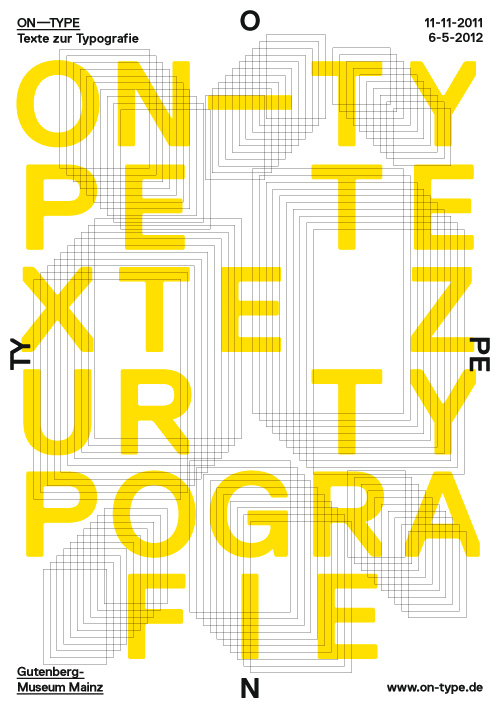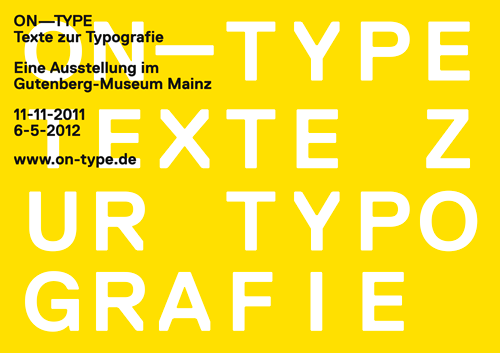
Die Ausstellung »ON–TYPE: Texte zur Typografie« präsentiert Klassiker der Typografiegeschichte des 20. Jahrhunderts und aktuelle Beispiele, auch aus den Beständen des Gutenberg-Museum Mainz und der Gutenberg-Bibliothek. Zum ersten Mal wird eine Sammlung von Grundlagentexten über die Schriftgestaltung zusammengestellt und den Besuchern vorgestellt.
Aus dem Pressetext: Typografie – die kleine Schwester der Sprache – ist ein Fundament unserer Kultur. Sie ist gegenwärtig. Sie gestaltet unser alltägliches Leben in der Zeitung, im Buch, auf den Preisschildern der Supermärkte und wird doch höchstens unterbewusst wahrgenommen.
Wenn wir als Kind die Buchstaben einmal erlernt haben, erschließen uns die Schriftzeichen die geschriebene Welt. Ähnlich wie beim Gehen oder Fahrradfahren lesen wir, nach ausreichender Übung, nahezu automatisch. Die Schrift nehmen wir dabei in der Regel kaum wahr – und doch besitzt jeder Leser reiche Erfahrungen mit der Schrift und jeder Schreibende hat auf seinem Computer Zugang zu einer Fülle unterschiedlicher Schriften.
Schriftliebhaber, Philosophen, Typografen und Schriftgestalter haben schon immer über Typografie weit mehr geschrieben, gestritten und gedacht als allgemein bekannt. Die Ausstellung »ON–TYPE: Texte zur Typografie« versammelt Thesen, Manifeste und Standortbestimmungen zur Typografie des 20. Jahrhunderts im deutschsprachigen Raum. Sie präsentiert Schriftmuster und Typo-Insider-Magazine, zeigt wichtige Protagonisten und Diskurse der Typografiegeschichte, bildet aber auch hitzige Diskussionen ab: über »deutsche Schrift«, den »modernen Menschen«, Lesbarkeit, Kleinschreibung oder die Folgen der Digitalisierung. Die Ausstellung vermittelt die Faszination der Schriftgestaltung. Eine eigens gestaltete Lese-Lounge, interaktive Anwendungen und Hörbücher laden ein zu einer intensiven Lektüre und Anschauung. Begleitet wird die Ausstellung von zahlreichen Vorträgen, Lesungen, Filmen, Workshops und einer Publikation.
Ein Projekt des Gutenberg-Museums Mainz Gutenberg-Museum Mainz in Kooperation mit Kommunikationsdesignern der Fachhochschule Mainz und des Instituts Designlabor-Gutenberg im Rahmen »Mainz – Stadt der Wissenschaft 2011«.
ON–TYPE – Texte zur Typografie
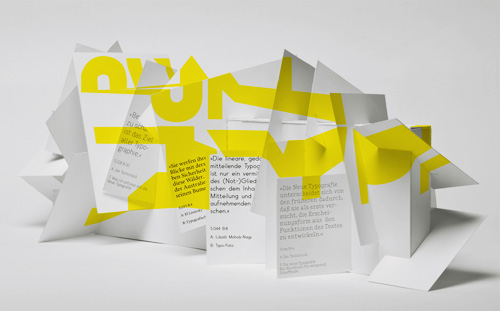
Während der Dauer der Ausstellung ON-TYPE gibt es ein großes Rahmenprogramm, das wir an dieser Stelle schon einmal kurz ankündigen möchten. Wir werden auf die ein oder andere Veranstaltung auch nochmals separat hinweisen.
TypoTour
decodeunicode
Die Schriftzeichen der Welt
Vortrag von Prof. Johannes Bergerhausen, Fachhochschule Mainz im Vortragssaal des Gutenberg-Museums
Wie vermehren sich eigentlich Bücher?
Type in Action
Workshop zur Typografie, jeweils 14.30 bis 18.00 Uhr, mit Max Kostopoulos und Jan Erlinghagen, Master-Studenten der FH-Mainz. Der Workshop stellt aktuelle Beispiele aus dem Bereich experimenteller Typografie vor und vermittelt Teilnehmern schriftgestalterische Entwurfstechniken: Buchstaben werden gezeichnet, abfotografiert, geritzt, digital gestreckt, gebogen, gescannt etc. Für Jugendliche im Alter von I5 bis I8 Jahren. (Ausstellungssaal) Voranmeldung erforderlich unter 06131/12 26 86. Eintritt: 6€
Buchkunde für Kinder
Buchgestaltung und -herstellung für Grundschulkinder mit Karin Schmidt-Friderichs, Verlag Hermann Schmidt Mainz (Museum), Voranmeldung erforderlich unter 06131 / 12 26 86. Kosten Museumseintritt.
Helvetica Kinoabend
Dokumentarfilm mit Kultstatus über Typografie und Grafikdesign. Der Film erzählt die Geschichte, Anwendung und Verbreitung der Schrift Helvetica (Regie: Gary Hustwit; England 2007). Kinosaal des Gutenberg-Museums. Im Anschluss an die Filmvorführung können im Foyer eigene Helvetica Postkarten gedruckt werden.
TypoTalk
Gespräche über Schrift
Ständig entwickeln Schriftgestalter und Grafikdesigner neue Schriften und das trotz der Masse an bereits verfügbarer Schriften. TypoTalks lässt Schriftentwerfer zur Wort kommen. Sie stellen sich und ihre Arbeit vor und erzählen was sie motiviert und inspiriert. Organisation und Durchführung: Marcel Häusler, Fachhochschule Mainz.
Symposium zum Thema Typografie & Macht
Wie heißt die Schrift auf den Plakaten? Sehe sie in letzter Zeit öfters und habe den Namen leider vergessen!
das ist die wunderbare REPLICA by NORM